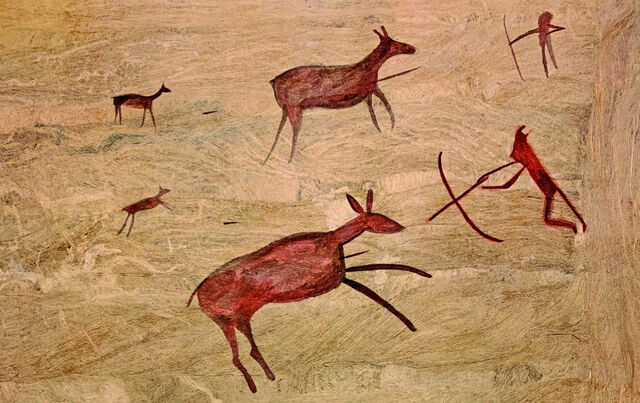
Una de las manifestaciones artísticas mas antigua
Se escribió originalmente sobre tablillas de arcilla húmeda
Fueron un sistema de escritura inventada por los antiguos egipcios basado en pictogramas
Los chinos desarrollan la caligrafía y usan logogramas
Los Fenicios desarrollan el proto alfabeto
Toman el alfabeto Fenicio y agregan vocales
Los romanos agregan las letras G,Y,Z separan las palabras y establecen sistema de puntuación
China Tsai Lun crea el papel con seda y lino
Johann Gensfleisch Zum Gutenberg desarrolla en Alemania una técnica para elaborar moldes de tipos móviles metálicos que se utilizarían para la impresión de letras individuales
Inicio la estandarización del tamaño de los tipos con la publicación del primer sistema de medición tipográfica